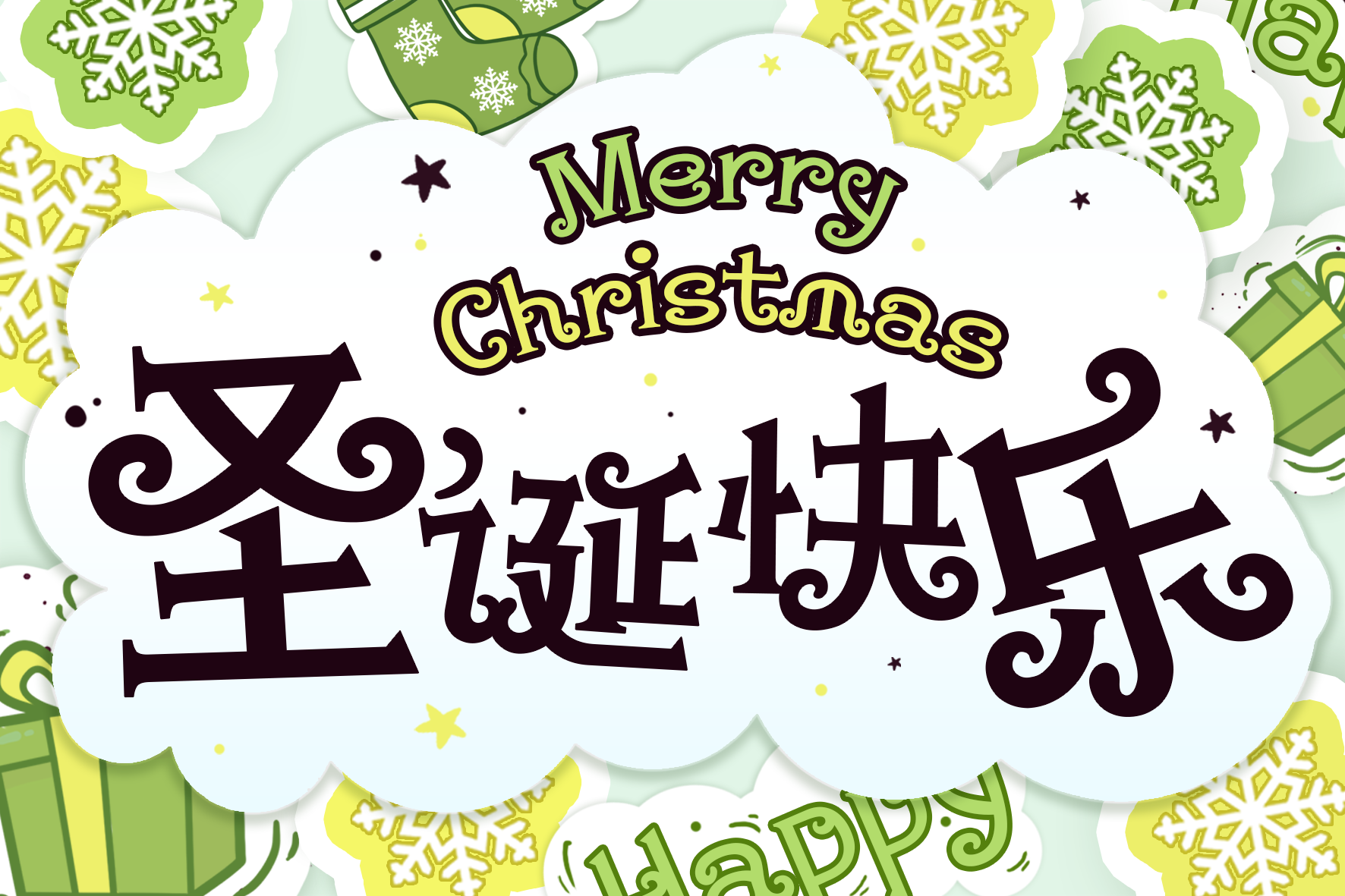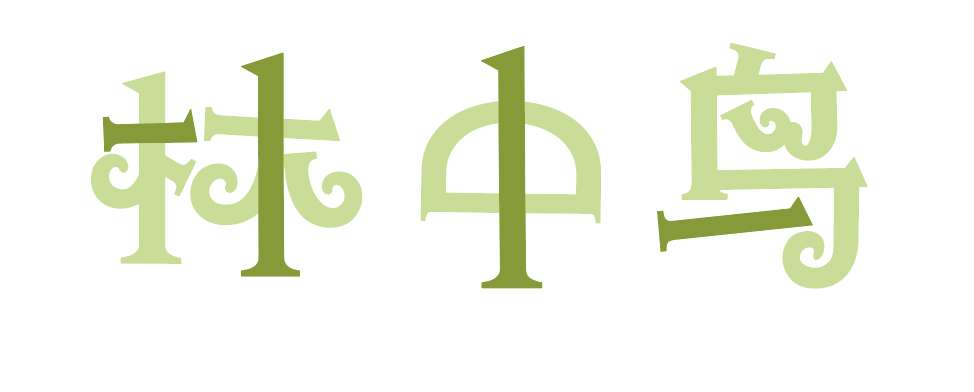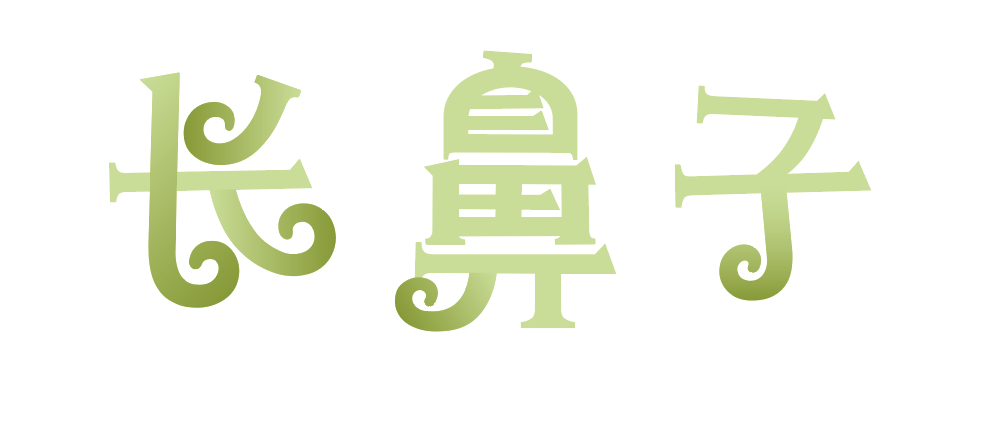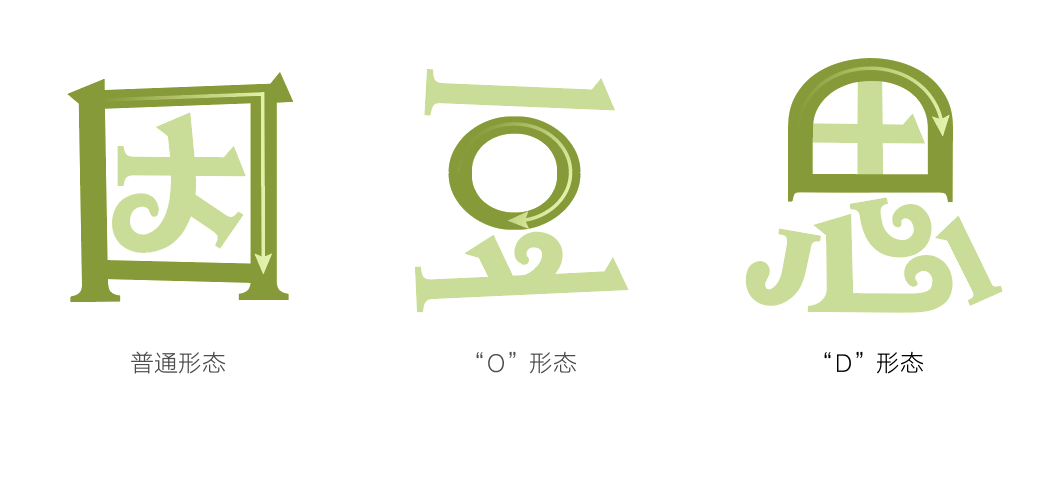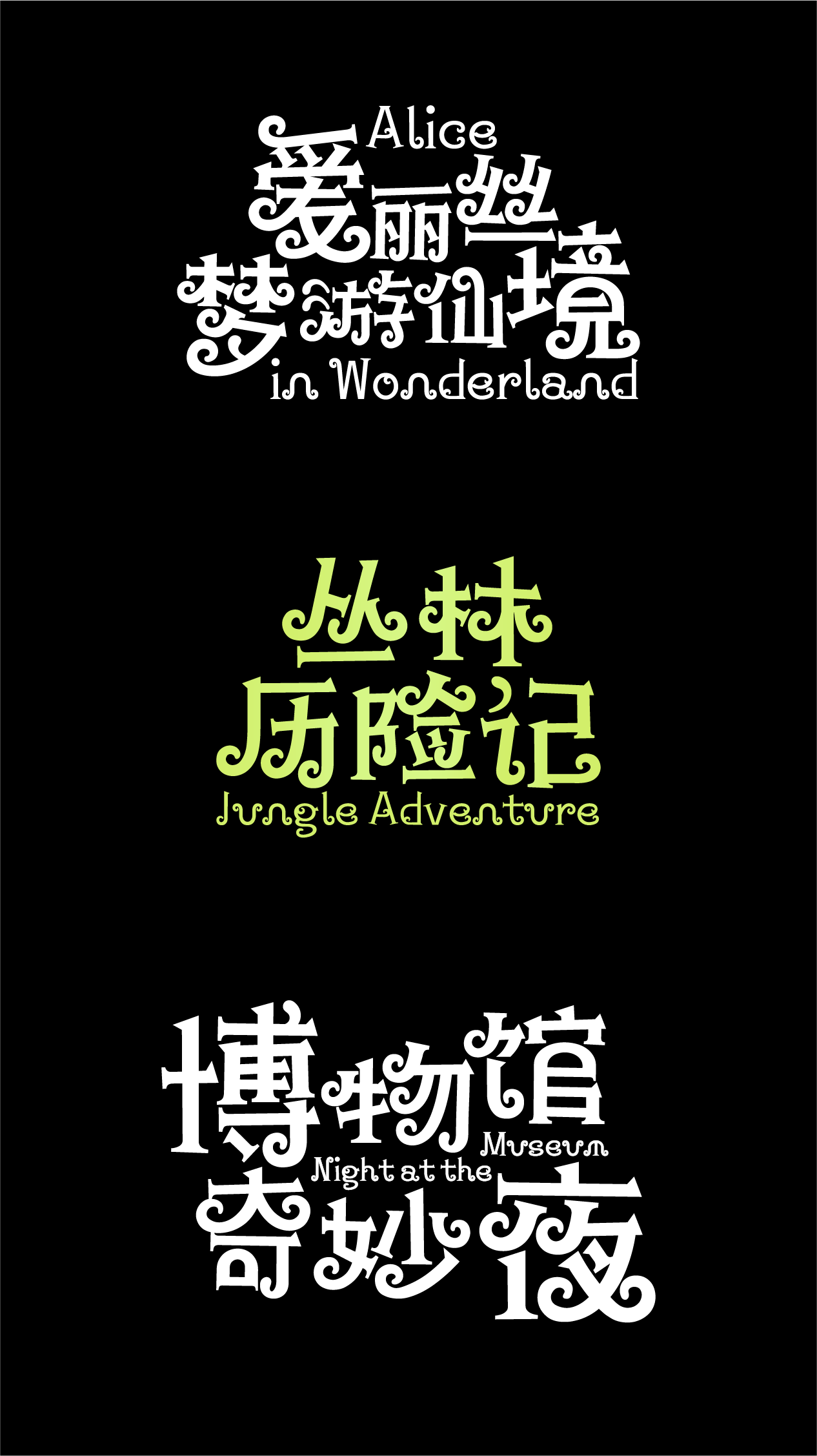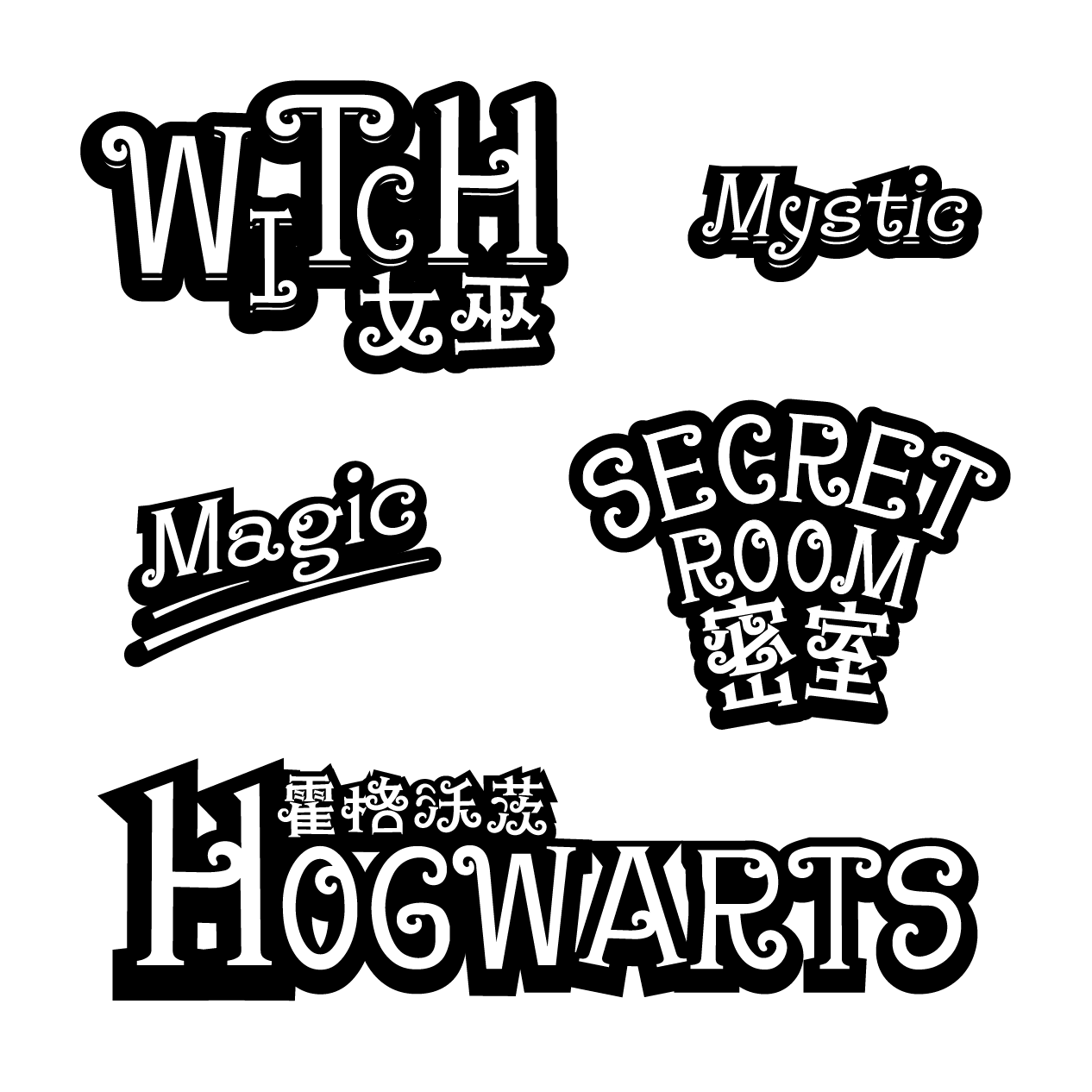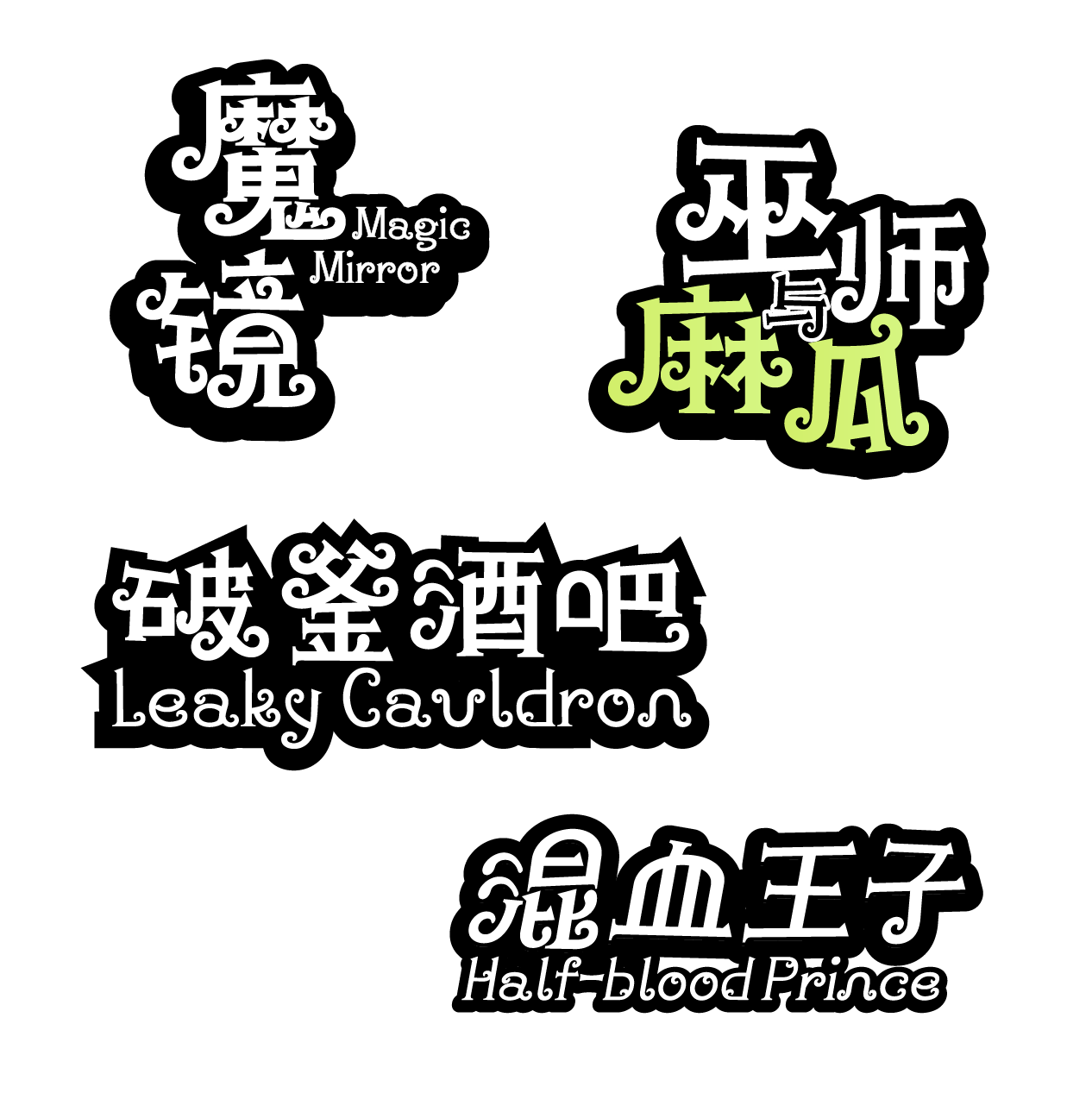
汉仪铸字魔法棒字体介绍,汉仪铸字魔法棒设计灵感
奇幻 / 神秘 / 活泼 / 趣味 / 卡通
品牌广告 / 游戏动漫 / 产品包装 / 娱乐综艺 / 书籍封面 / 标志LOGO
汉仪铸字魔法棒 | 魔幻字体
“汉仪铸字魔法棒”是汉仪旗下的“铸字社工作室”打造的一款集趣味性和装饰性于一体的创意字体。它的性格活泼好动,字形奇幻多变,无论是笔画还是装饰元素,都有着强烈的卡通意味。使用这款字体会为你的设计增添更多趣味。
汉仪铸字魔法棒 | 形态多变
“汉仪铸字魔法棒”的字形变化多样,依据字体结构而呈现出或长或方或扁的节奏变化。
汉仪铸字魔法棒 | 笔画灵动
“汉仪铸字魔法棒”的笔画横细竖粗,笔画与数字“1”的造型相似。
“汉仪铸字魔法棒”撇、捺和钩画的尾端有着不同弯曲程度的“小勾”装饰,像变色龙的尾巴一样,显得字体灵动俏皮。
“汉仪铸字魔法棒”部首“口”字旁的造型多变,依据不同的字体结构设定了三种形态。
汉仪铸字魔法棒 | 变宽字体
由于“汉仪铸字魔法棒”不同文字的字面差异较大,考虑到排版使用上的体验感,我们在技术上采用了字间距变宽的处理方式,使字体的排版效果更加舒适自然。
汉仪铸字魔法棒 | 中西文匹配
“汉仪铸字魔法棒”的西文字母有着和中文一样灵活多变的装饰元素,中西文搭配使用十分和谐。